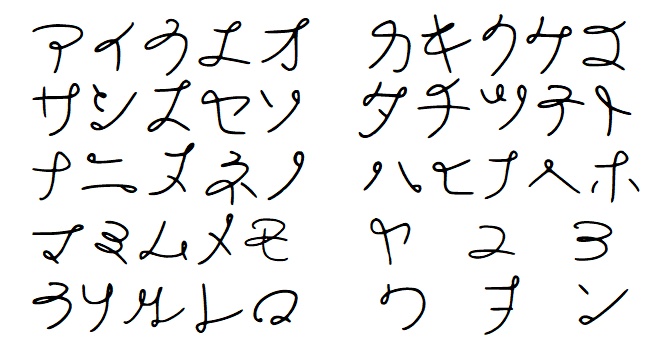
(試作品)ロールフォント 手書き
片仮名のみの試作品です。 需要(連絡)があれば、文字追加します。(多分) https://twitter.com/kobene_ (その他フリーフォント)↓↓↓ https://kobene.booth.pm/items/722252 利用規約を確認してからダウンロードしてください。 商用利用をお考えの方は使用許諾をしっかり確認の上、必要に応じ問い合わせるなどしてください。 フリーフォントですが、著作権は放棄していません。 作者を偽る行為、再配布、フォントの販売などは禁止です。